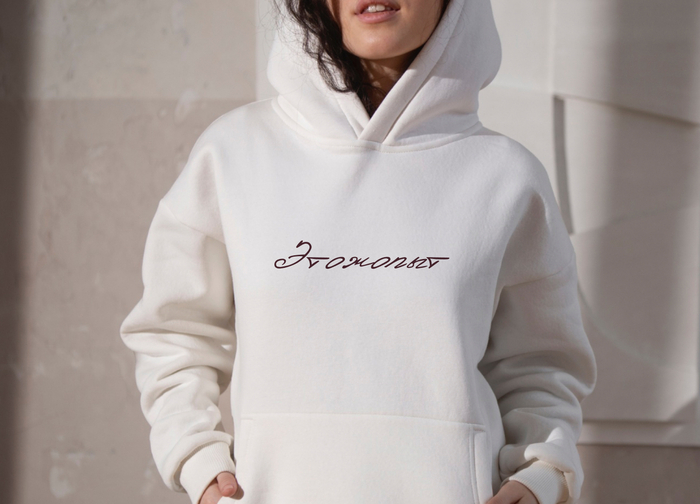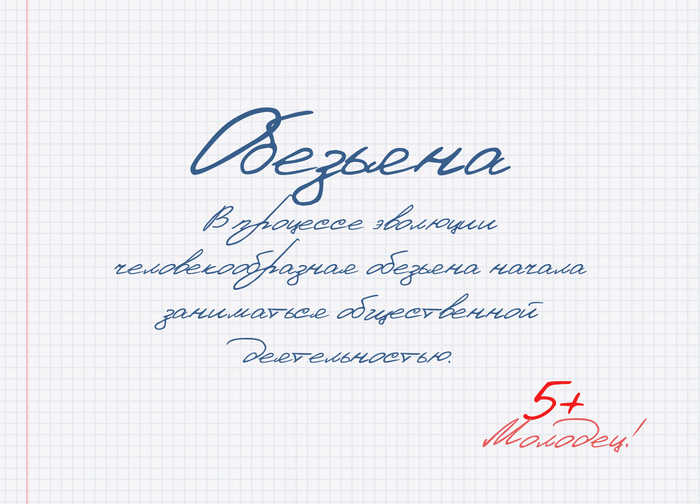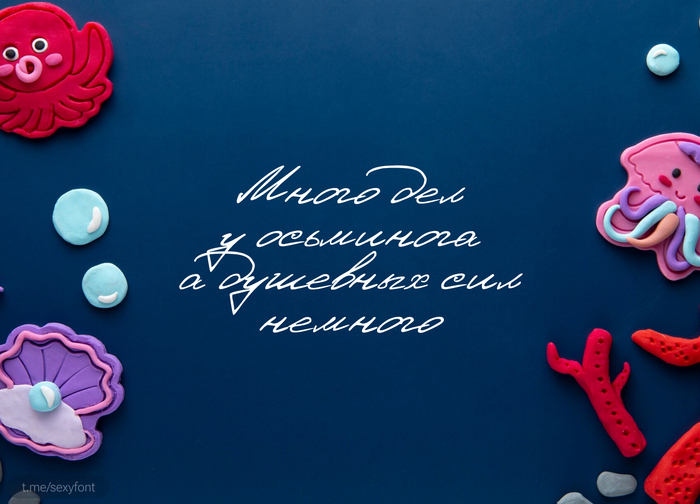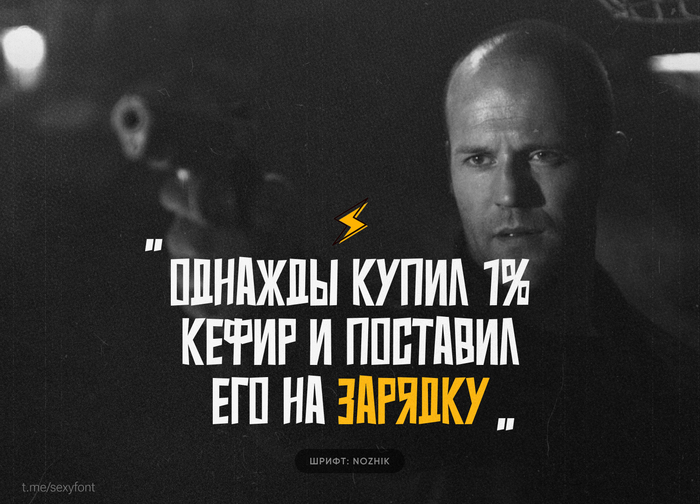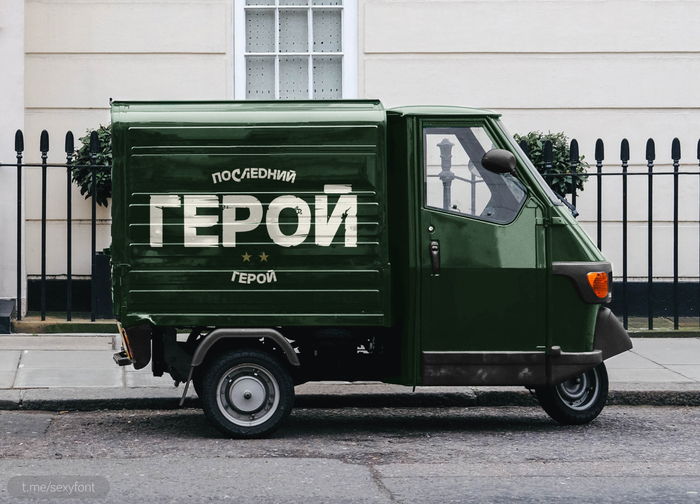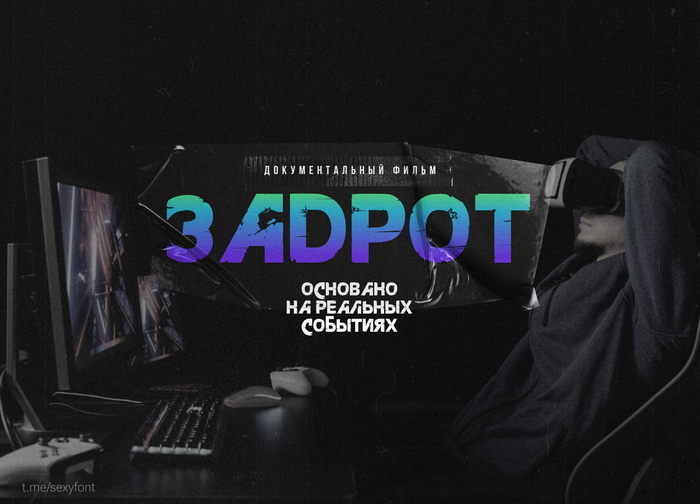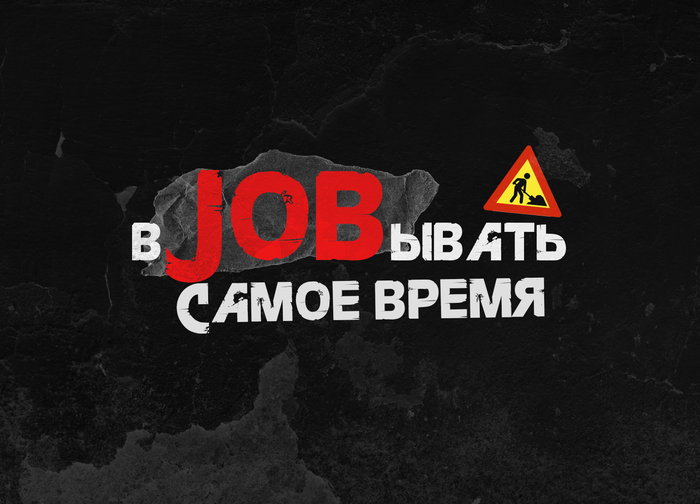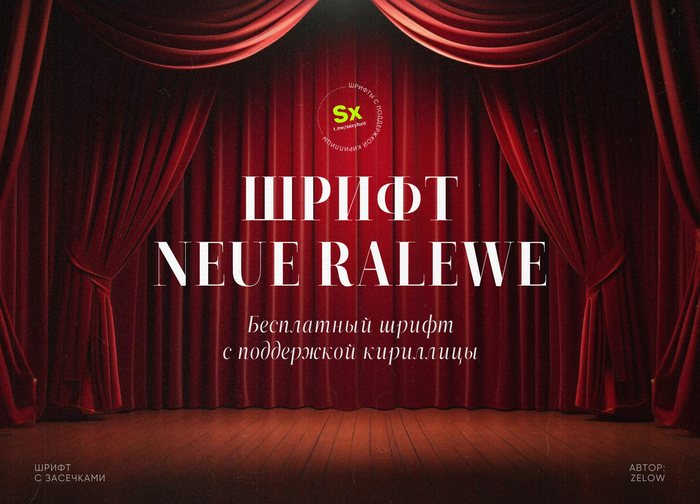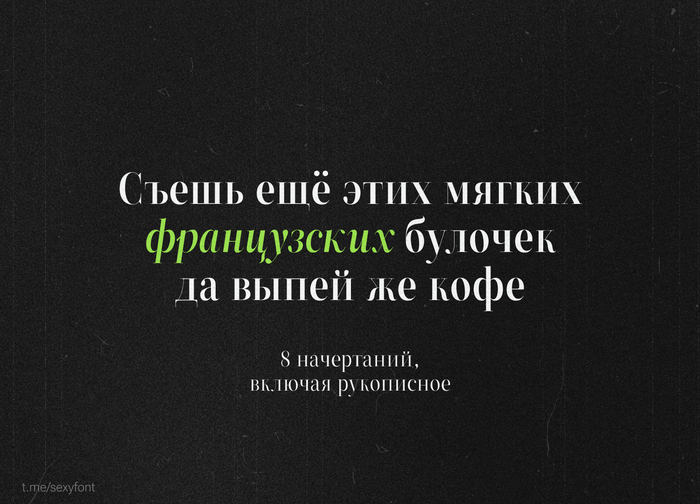
Подборка шрифтов в цитатах Стейтхема
Э, Йо! Стетхем на связи! Вторая часть угольных шрифтов для твоих проектов. Цитаты в виде народного творчества с комментариев аккаунта Стейтема.
Курсивный, открыточный шрифт florisel script
Шрифт из игры Far Cry
Шрифт Far Cry. Кириллица из известной игры. Кто играл? Какая твоя любимая часть?
Подборка шрифтов в старом стиле
Что-то старославянское, что-то не славянское. Сам решишь уже)
Шрифт ZT Neue Ralewe
Приует! Давненько у нас не пробегало антиквы. Вот, поймал одну. Держи крепче. Шрифт ZT Neue Ralewe и моя фирменная презентация. Есть аж 10 начертаний!
Шрифт Vivl rail. Кириллица
Vivl rail. Кириллический шрифт со строгими начертаниям. Хорошо подходит для коротких заголовков на футуристические темы.
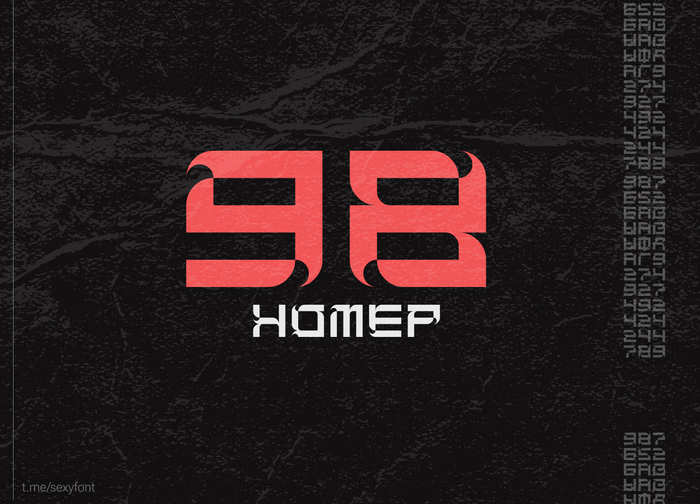
Шрифт Denistina
Рукописный шрифт как со школьной тетради) В меру аккуратный. Использовать только в коротких фразах. Как и большинство подобных шрифтов читаемостью не блещет.
Шрифт blos
Бесплатный шрифт с интересными узорами. Особенно в цифрах)